エレガントなスクリプト書体29セットを収録し、1セットあたり1ドルで合計29ドルとお買い得なコレクション。ペアリングフォント・イラスト・ロゴテンプレートなどのおまけもたくさん入っています。
「The Bespoke Font Collection」の気になる内容
▼「The Bespoke Font Collection」のフォント一覧はこちらです。
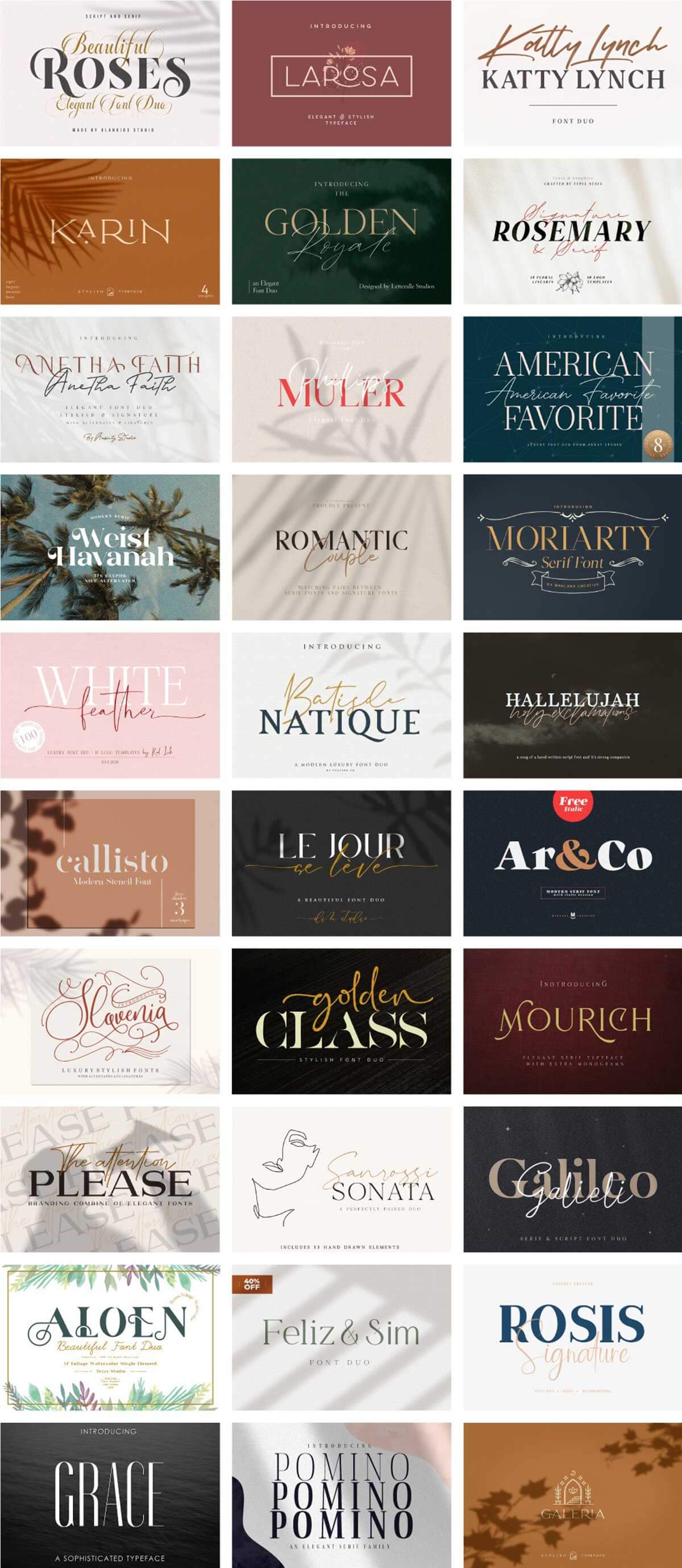
今回のバンドルの中で、私が特に気になるフォントはこちらです。
Beautiful Roses – Font Duo
「Beautiful Roses – Font Duo」はウェイトの強弱がハッキリしたセリフ書体とスクリプトフォントのセット。ブランディングやロゴづくりにあると便利なフォントです。
Golden Class // A Stylish Font Duo
ところどころ欠けた部分が特徴的な「Golden Class」。ペアのスクリプト書体もおしゃれで、ポスターなどで大きく使うと注目を集めそうなフォントです。
Weist Havanah – Modern Serif
デザイン性の高いサンセリフフォント「Weist Havanah」。連字や字形のバラエティも豊富なのが高ポイント。結婚式の招待状や名刺などのデザインに役立ちそうです。
Callisto — Modern Stencil Font
読める限界までパーツを削った「Callisto」。regularと少し線を足してわかりやすいhalfの2パターンを収録しており、用途に合わせて使い分けられます。
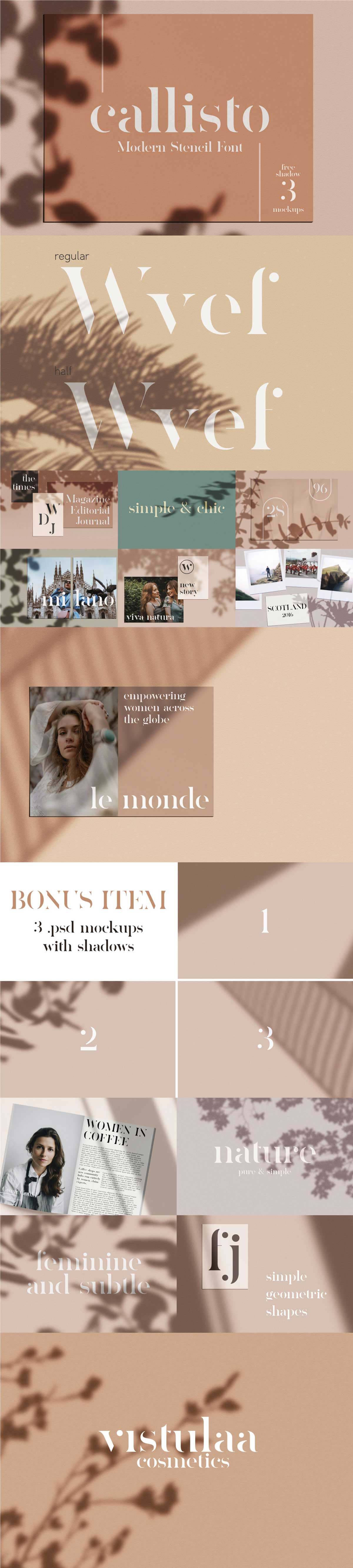
Mourich Elegant Font | With Extra
大胆な連字のデザインがユニークな「Mourich Elegant Font」。アルファベットのコンビネーションパターンも多数用意されています。レストランのメニューやロゴ作成に便利なフォントです。
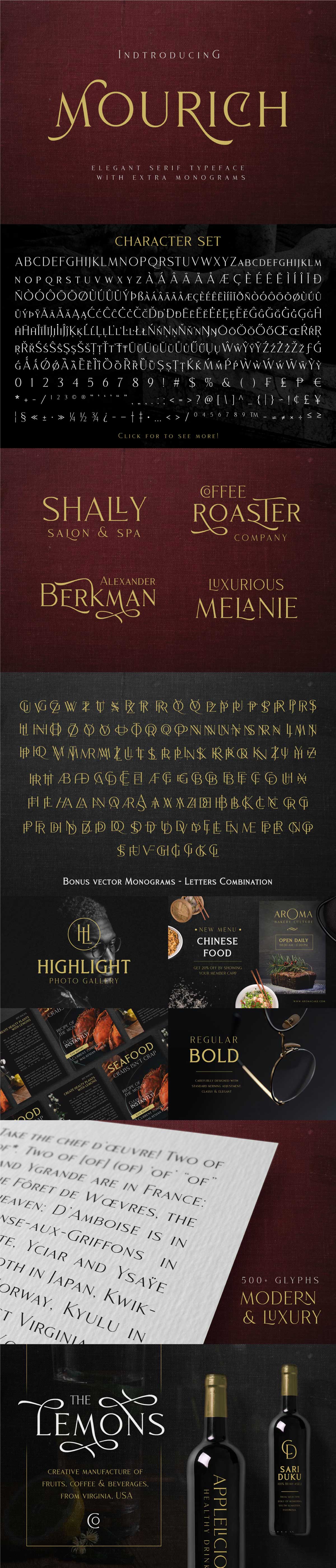
Slovenia
大胆なタイポグラフィが楽しめる「Slovenia」。用意された飾りと組み合わせれば、一見複雑なロゴやメッセージのデザインも時間をかけずに出来上がります。